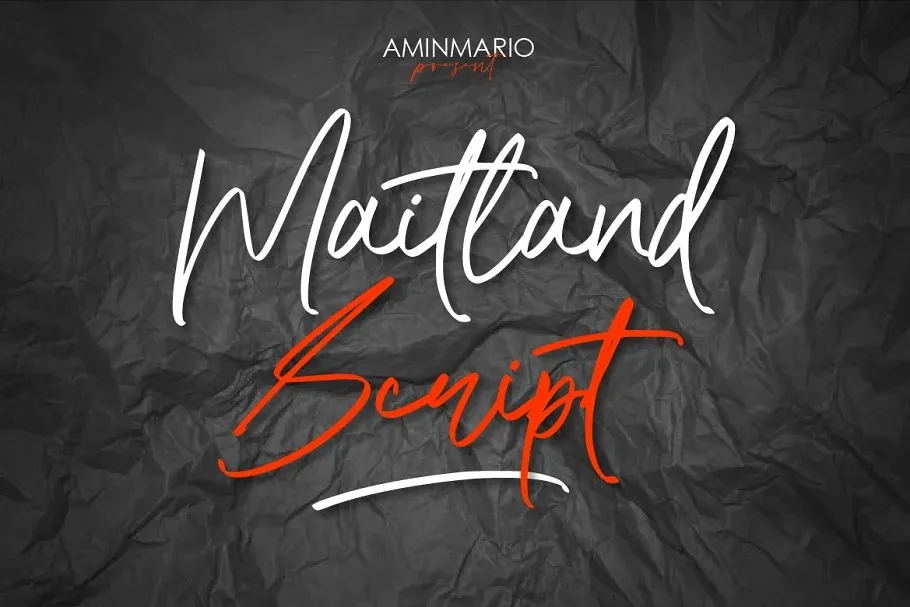
Maitland é uma fonte script criada pelo designer Aminmario que traz estilo moderno à sua escrita, com uma pitada casual e sofisticada. Conhecida por seus feitos de OpenType, esta fonte tem a capacidade única de transformar qualquer texto em uma arte fluida e elegante. Ela é perfeita para designers buscando um toque delicado e contemporâneo, ideal tanto para nomes de negócios quanto para trabalhos que exigem um ar refinado e versátil. Sua graciosidade natural e sua disposição fluida fazem dela uma escolha excepcional para qualquer projeto em que você deseja adicionar sofisticação ao texto. Confortável para o olho, Maitland é a fonte perfeita para quem busca um equilíbrio entre modernidade e elegância em seus designs.